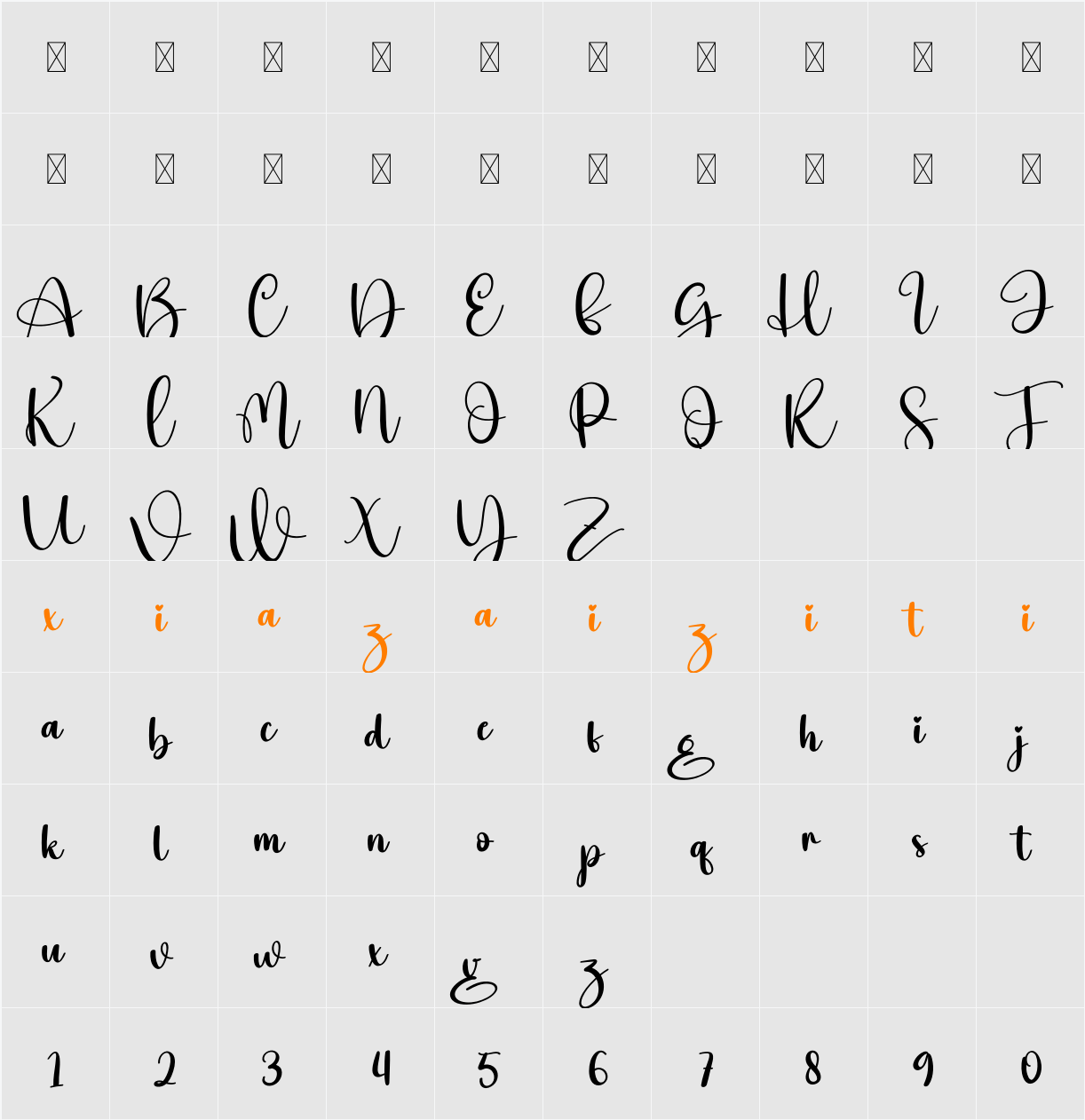
Hey Marge
Hey Marge,这款字体结构工整、笔画清晰,兼顾美观与易读性,适用于标题、正文、海报、包装、LOGO 等多种场景。字形优雅稳定,风格百搭耐看,适配日常排版与创意设计,让文字呈现更舒适、更具质感。Hey Marge一笔一画,皆是细节,以均衡的比例、流畅的线条打造舒适视觉体验,字形端正大气,风格简约现代。无论是商业设计、品牌宣传还是日常排版,都能轻松驾驭,让文字更有格调与力量。Hey Marge字体下载。